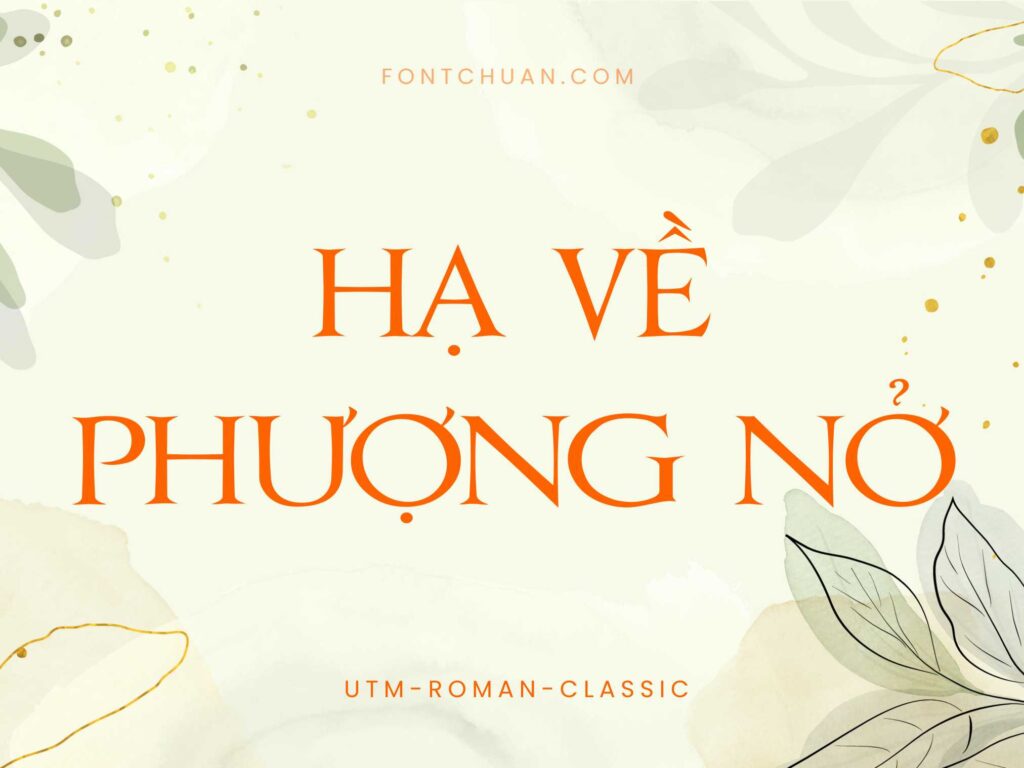
Font UTM Roman Classic Việt Hóa
UTM Roman Classic là một font chữ serif mang phong cách cổ điển và trang trọng, được thiết kế với những đường nét tinh tế, giúp tăng tính chuyên nghiệp trong các thiết kế đồ họa. Font này lấy cảm hứng từ những kiểu chữ La Mã cổ đại, mang đến cảm giác thanh lịch và truyền thống. Font đã được Việt hóa để hỗ trợ tiếng Việt, giúp mở rộng khả năng ứng dụng. Thành viên của Font Chuẩn đã sưu tầm và giới thiệu font này nhằm đáp ứng nhu cầu bạn đọc, cung cấp nguồn tham khảo chất lượng và ứng dụng thực tế vào các dự án thiết kế
Về đặc điểm thiết kế, UTM Roman Classic có kiểu chữ serif thanh mảnh, độ tương phản cao và các đường nét cân đối, tạo nên sự sang trọng và dễ đọc. Font này phù hợp với nhiều ứng dụng như thiết kế logo, tiêu đề, bìa sách, tài liệu chuyên nghiệp và nội dung thương hiệu. Các ngành nghề như quảng cáo, giáo dục, thiệp cưới và công nghệ có thể tận dụng font này để tạo nên sự đẳng cấp và chuyên nghiệp trong các sản phẩm thiết kế
Tác giả: Erik Van Blokland
Việt hóa: Bdesign